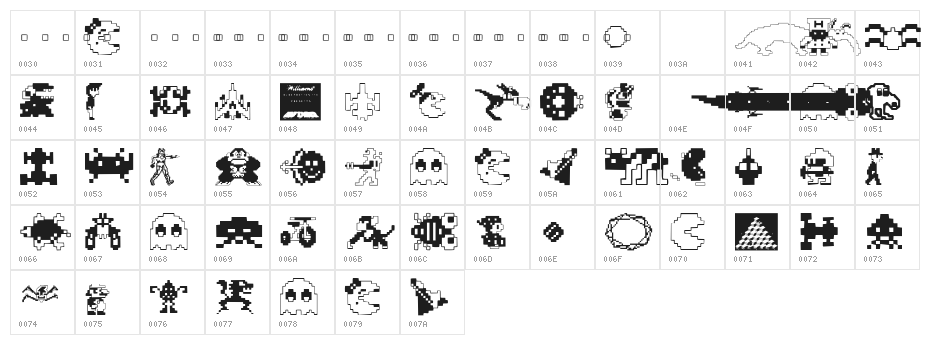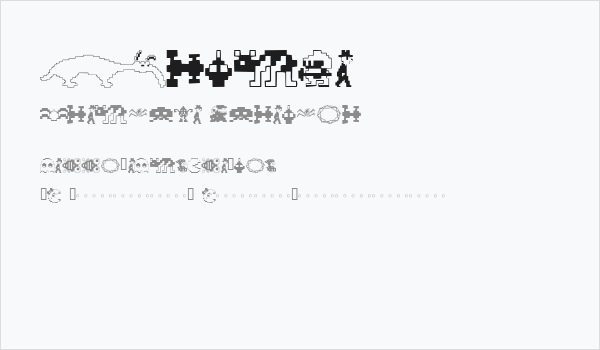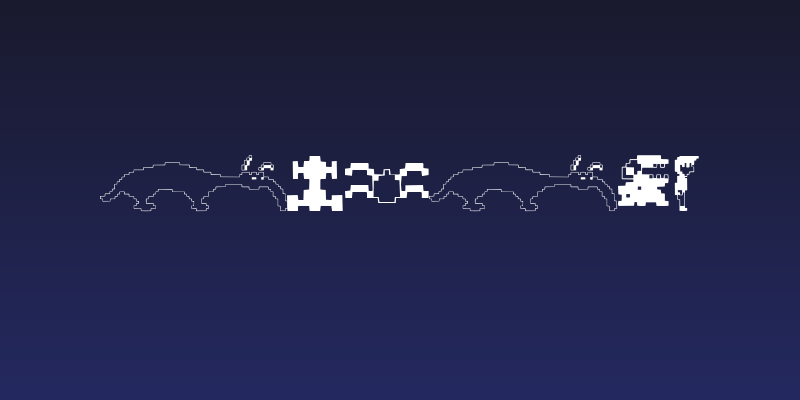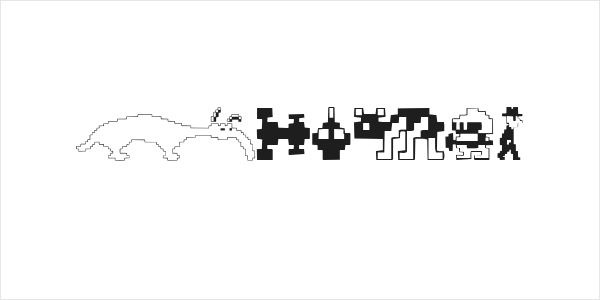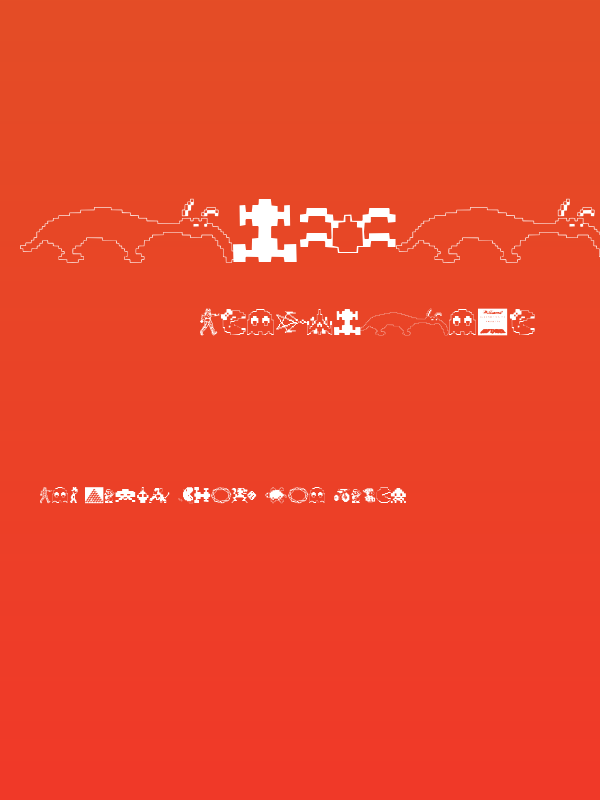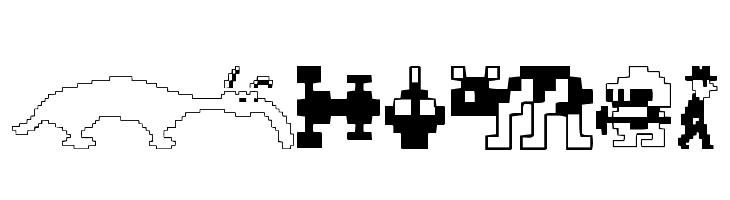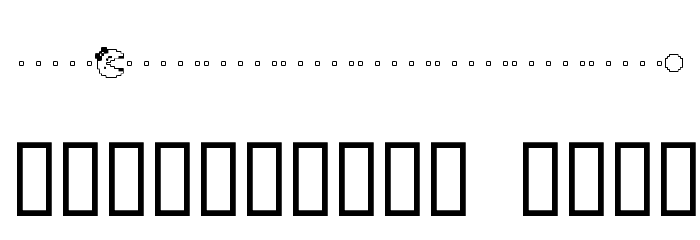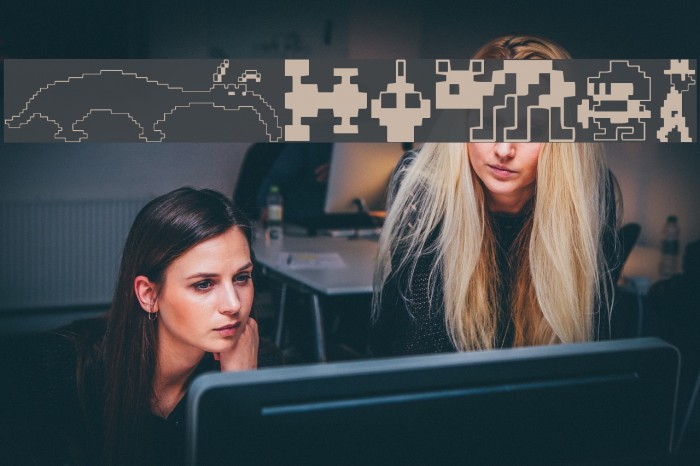
Arcade Font
✎ Pixel
| श्रेणियाँ | Pixel |
| समग्र शैली | Vintage |
| उपयोग का मामला | Logos, Posters, Merchandise |
| सुझाए गए प्रोजेक्ट | Ideal for retro-themed designs, video game events, posters, and merchandise that celebrate classic gaming culture. |